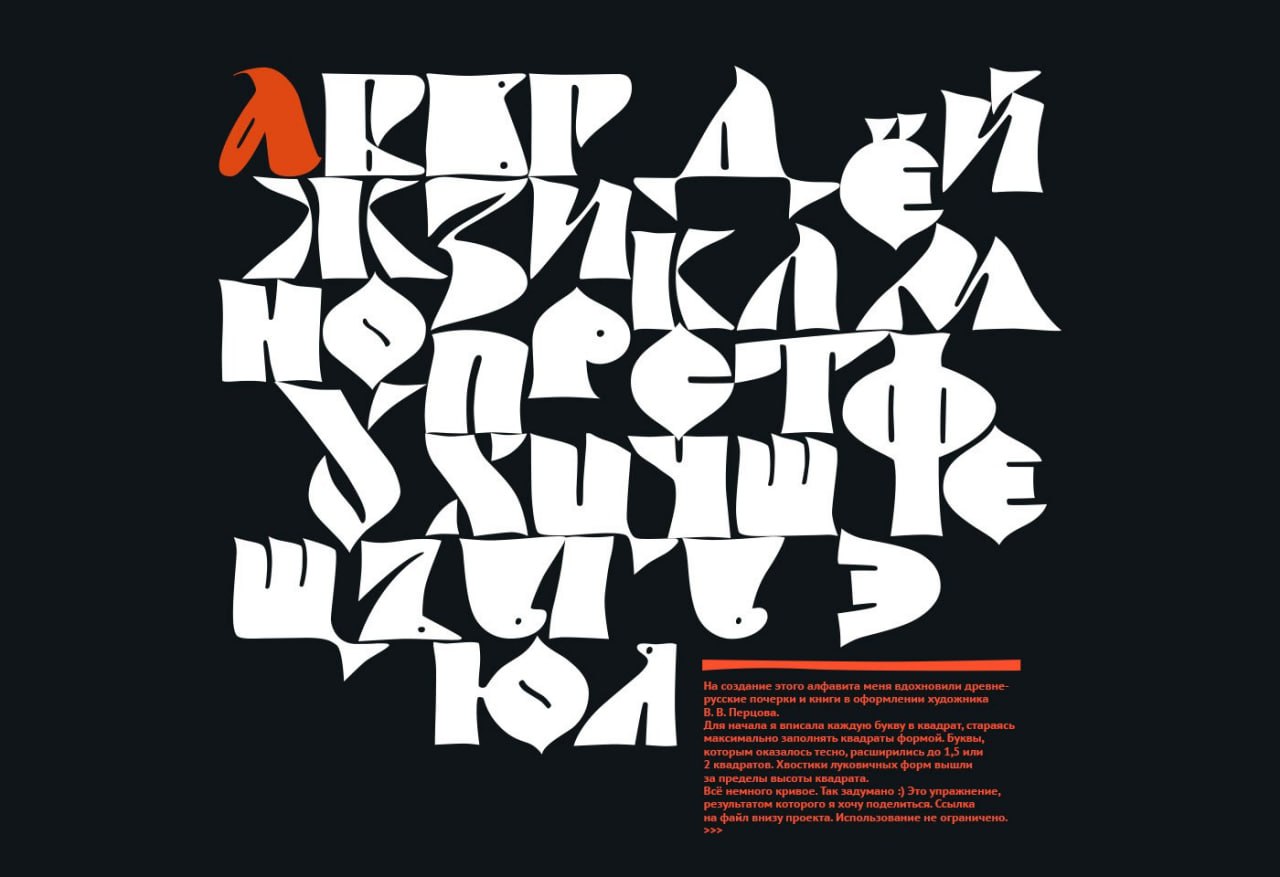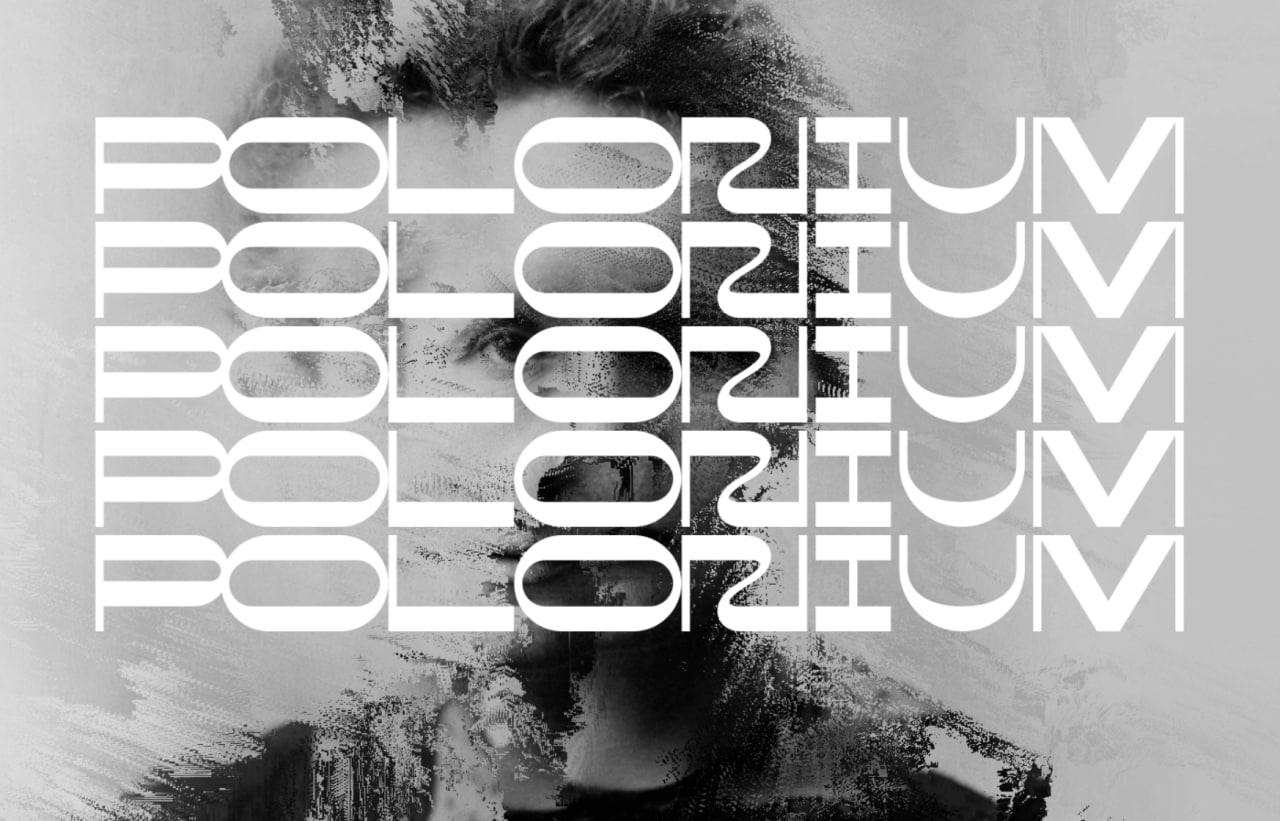
Шрифт "Univermag" by Andrew Hnutov Шрифт от дизайнера из Украины, при его создании он вдохновлялся вывеской Харьковского ЦУМа. Есть поддержка кириллицы, цифр и всех спец. символов. Бесплатен для личных и коммерческих проектов.
Изящный шрифт в старо-славянском стиле, который подойдёт для узконаправленных проектов. Шрифт бесплатен для любого типа использования, а также поддерживает кириллицу и латиницу.
Unlimited Pie — это забавный, разнообразный и немного драматичный дисплейный шрифт. Благодаря своему уникальному характеру шрифт можно использовать везде. Шрифт содержит как латиницу, так и кириллицу и поддерживает 88 языков.
Необычный шрифт гротеск с острыми углами. Он по-своему красив, но нечитабелен и немного рябит глаза. Подойдет к короткому заголовку или на печати газеты, например.
Автор:
Valeriya Zherebyateva
Это дисплейный шрифт, который можно использовать в различных областях графического дизайна, но лучше всего он подходит для заголовков и дизайна логотипов.
Шрифт "Polonium "by Alexey Atapin При создании этого шрифта, дизайнер вдохновлялся историей открытия полония в 1898 году. Бесплатный для личного и коммерческого использования. Есть поддержка кириллицы, а также всех цифр и символов.
Шрифт "NEUTRAL FACE" by Vadym Aksieiev Шрифт без засечек с двумя вариантами начертания, Bold и Regular. Есть поддержка кириллицы. Бесплатен для личных и коммерческих проектов.
Шрифт "Onest" by Dmitri Voloshin Внутри архива вы найдёте 7 уникальных начертаний шрифта. Кириллица и латиница. Полностью бесплатен для личных и коммерческих проектов